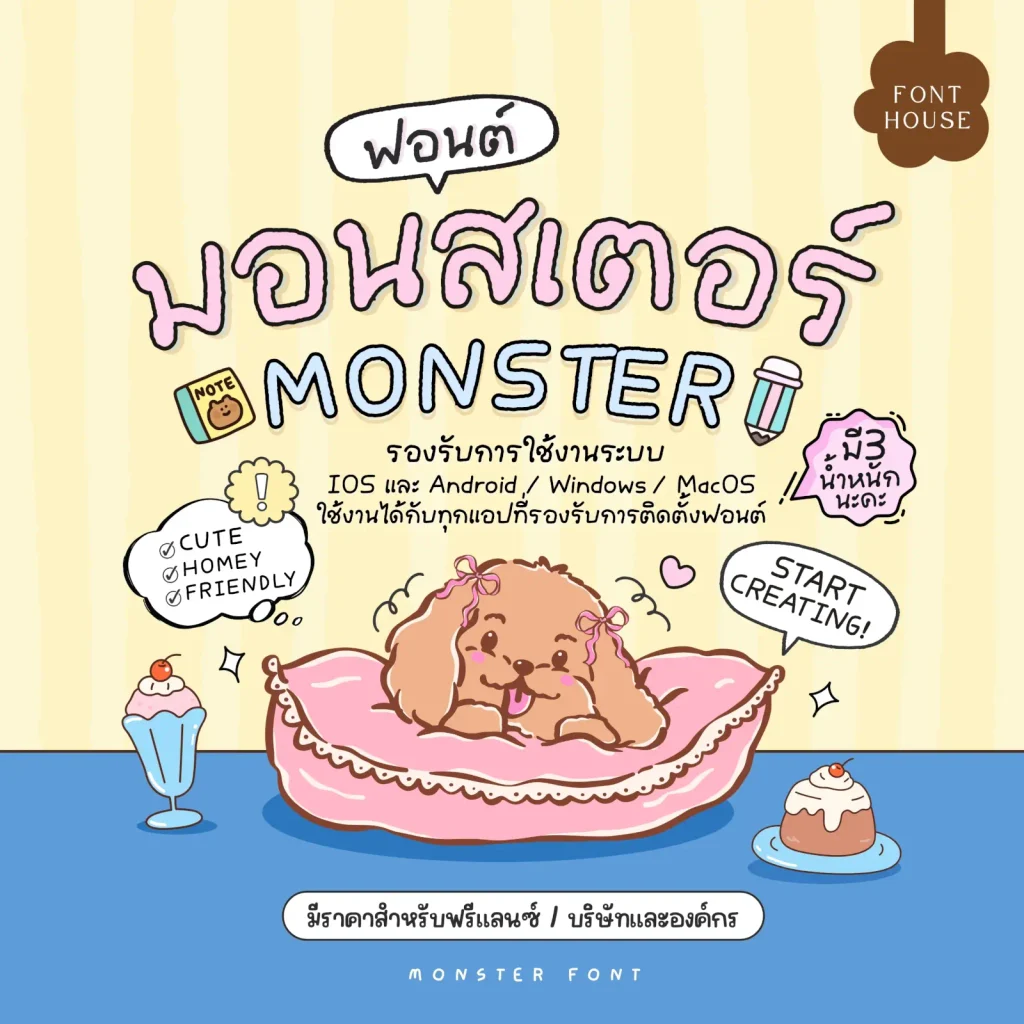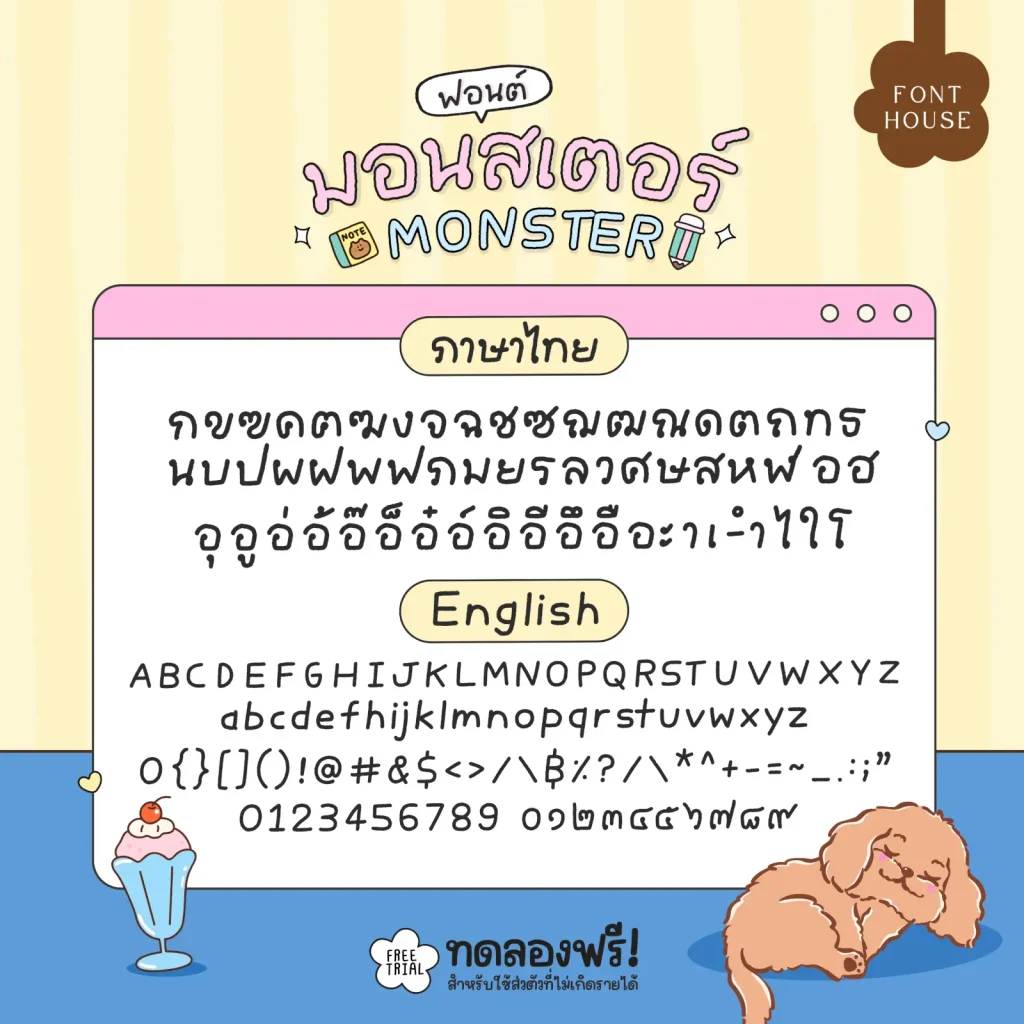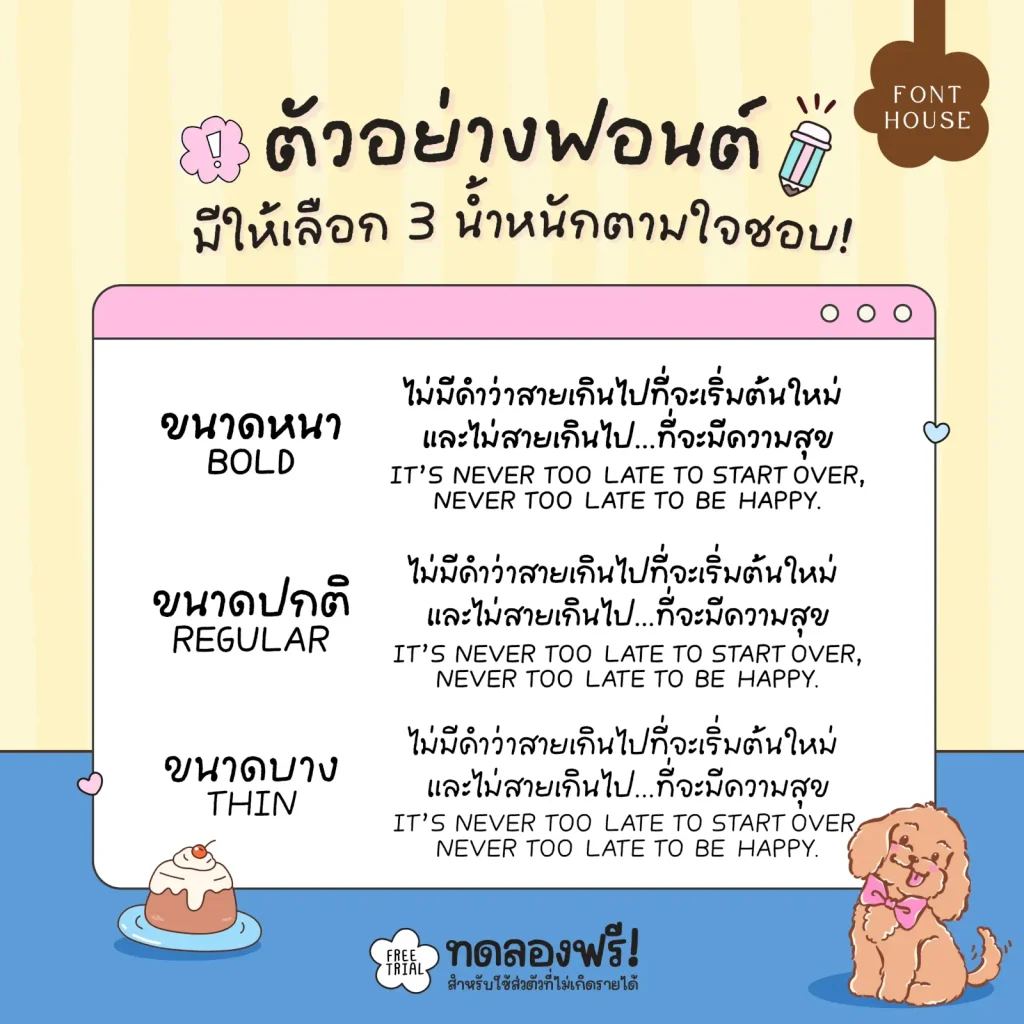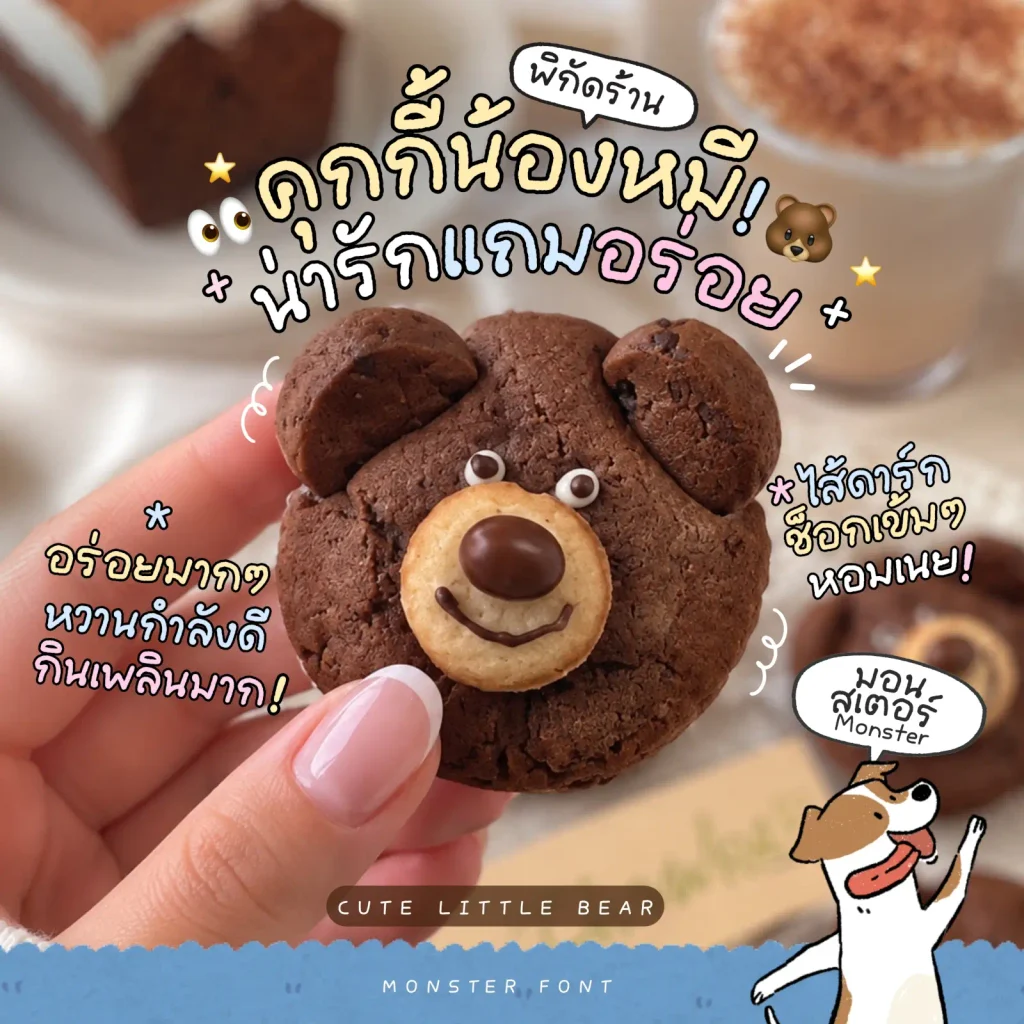
ฟอนต์ มอนสเตอร์ (FH Monster) – ด้วยลายเส้นจากแรงบันดาลใจในการเขียนด้วยดินสอ ให้ความรู้สึกเหมือนลายมือที่เขียนขึ้นด้วยมือจริง น่ารัก ซุกซน อบอุ่น และเป็นกันเอง เรียบง่ายแต่มีคาแรกเตอร์ เติมความขี้เล่นนิดๆ ให้ทุกงานดูน่ารักและมีชีวิตชีวามากขึ้น
- มี 3 น้ำหนัก
มอนสเตอร์ (FH Monster)